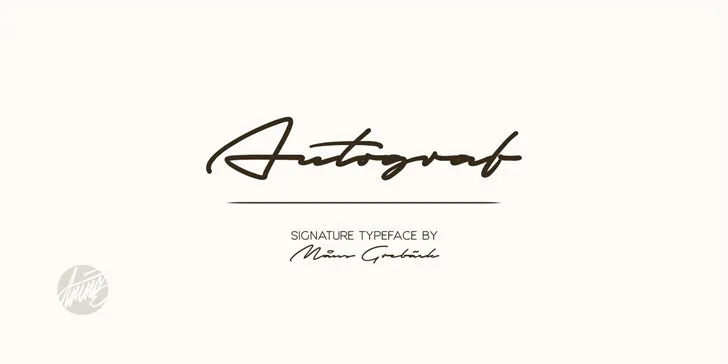
A ‘Autograf Font’ é uma elegante escolha para quem busca expressar seu design com suavidade e sutileza. Embora não seja uma fonte especialmente robusta ou elaborada, a ‘Autograf Font’ traz um ar de naturalidade ao texto, fazendo parecer que cada palavra foi escrita à mão por um artesão dedicado. Seus traços delicados permitem uma leitura confortável para o olhar humano, sem perder na qualidade gráfica que muitos designers esperam em um script font. Especialmente adequada para descrições e textos informativos no seu website ou redes sociais, a ‘Autograf Font’ é uma excelente opção para quem busca uma fonte personalizada e sofisticada. Seja você designer de sites, editor gráfico ou simplesmente criativo com sua escrita digital, esta font pode transformar seus projetos em verdadeiros trabalhos de arte digitais. A cada parágrafo escrito na ‘Autograf Font’, você está adicionando um toque delicado e encantador à sua mensagem. O designer Hamilton sabe que o uso certo da fonte pode fazer toda a diferença, seja para assinar um documento ou incorporar uma mensagem personalizada em seu site. Essa font é perfeitamente adaptável a qualquer estilo de design, desde as mais sutis até os mais ousados, oferecendo uma variedade de opções para quem deseja expressar suas ideias com confiabilidade e elegância através do texto digital.